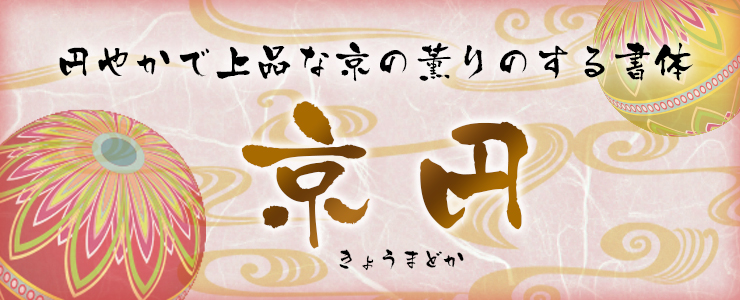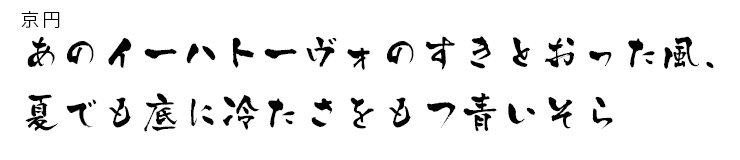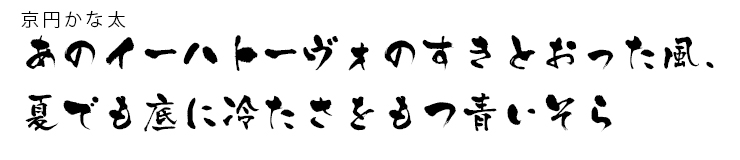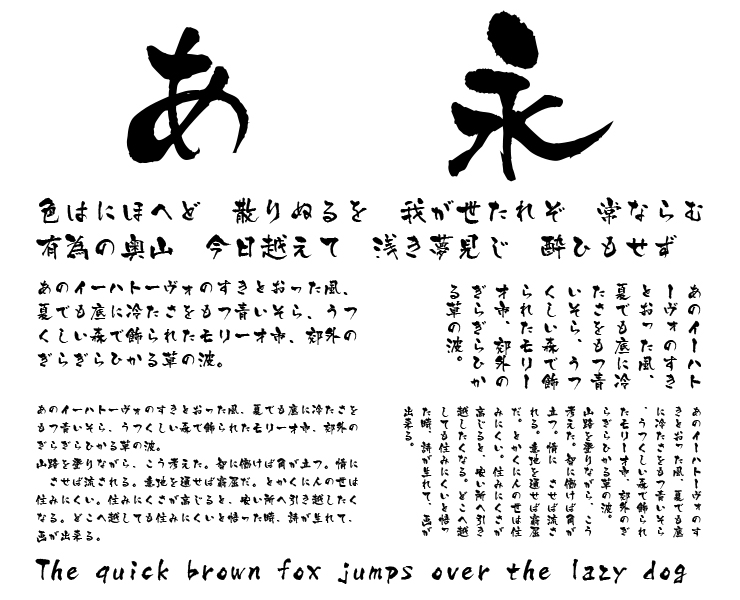
円やかで上品な京の薫り 京円
墨のにじみを生かした、
円やかで上品な京の薫りのする書体
憶えておいでの方もあろうかとは思いますが、
昔、京都の製菓会社から発売されていた
「きょうまどか」というおせんべいがありました。
昔懐かしい素朴で上品な、醤油のおせんべい。
そんなイメージで作られた「京円」の特徴や魅力についてご紹介します。
半紙に書かれた「京円」の原稿。文字の大きさや太さ、全体のテイストが見事に均一に書かれています。
京円とは
書家小林圓佳氏の字母により「白舟書体デザイン筆文字」の第二弾として誕生した「京円」。
小林氏自身の人柄が醸し出す、ほっこりとまあるい文字はこれまでに沢山の商品や広告のロゴに使用され、多くの支持を集めています。
小林圓佳
森山啓鄕氏に師事し、幼少から書を学び、22歳より実用書道・版下作家として活動。
大阪府印章技術展・全国印章技術大競技会などでの受賞歴多数。
日本印章協会版下一級・印章彫刻一級技能士。
小林圓佳 氏
書体の特徴
白舟書体の人気書体の一つである「」を表現するキーワードが「奇抜」「大胆」だとすれば、「京円」は「上品」「円やか」。
和風を意識したいロゴや題名によし、優しい文章を打つのによしの筆文字書体です。
また本書体は仮名(ひらがな・カタカナ)のみで使用するニーズに応えるため、仮名部分に太い文字を採用した「京円かな太」も同梱しています。